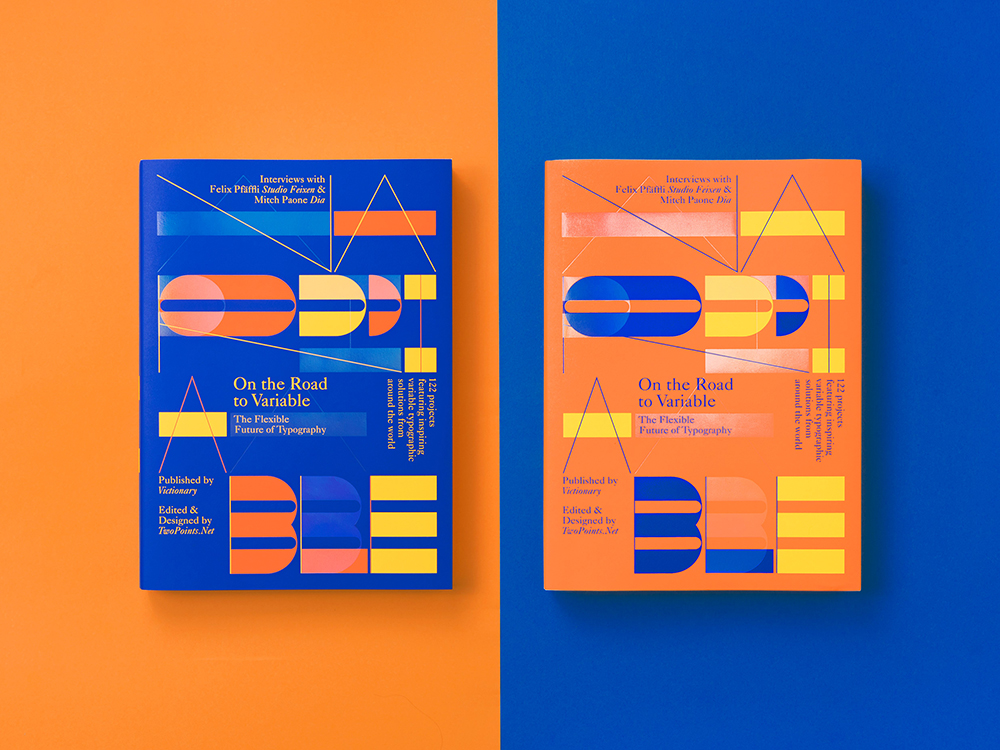
Una fuerza imparable en el diseño gráfico contemporáneo
En septiembre de 2016, Adobe, Google, Apple y Microsoft anunciaban una nueva actualización en el protocolo OpenType que permitiría que las fuentes sean variables. A partir de este punto, los diseñadores tendrían la libertad y flexibilidad para usar una amplia variedad de estilos. Aunque la tecnología aún no se ha implementado completamente, la tipografía variable ya se está convirtiendo en una fuerza imparable en el diseño gráfico contemporáneo.
On the Road to Variable: The Flexible Future of Typography explora, a lo largo de sus 264 páginas, una colección de trabajos ecléctica y emocionante que experimenta con la modificación de los tipos de letra existentes, así como la creación de otros nuevos para vislumbrar el futuro de la tipografía.
Este notable trabajo del estudio de diseño TwoPoints.Net recoge 122 inspiradoras piezas de creativos de todo el mundo, además de unas extensas y bien logradas entrevistas a Felix Pfäffli, de Studio Feixen y a Mitch Paone, de DIA. El volumen, de 19x 26,5 cm y tapa dura ha sido editado por la editorial británica Victionary. «La tipografía nunca ha sido tan flexible como lo es hoy, y estamos orgullosos de haber hecho un libro sobre un tema que merece ser profundizado», comenta Martin Lorenz, director de TwoPoints.Net.